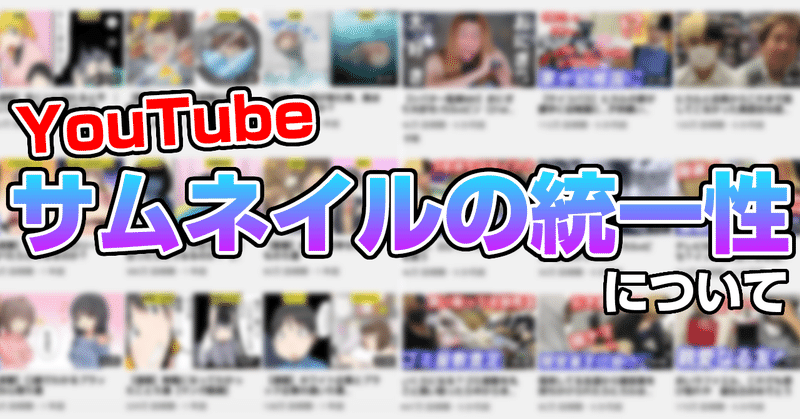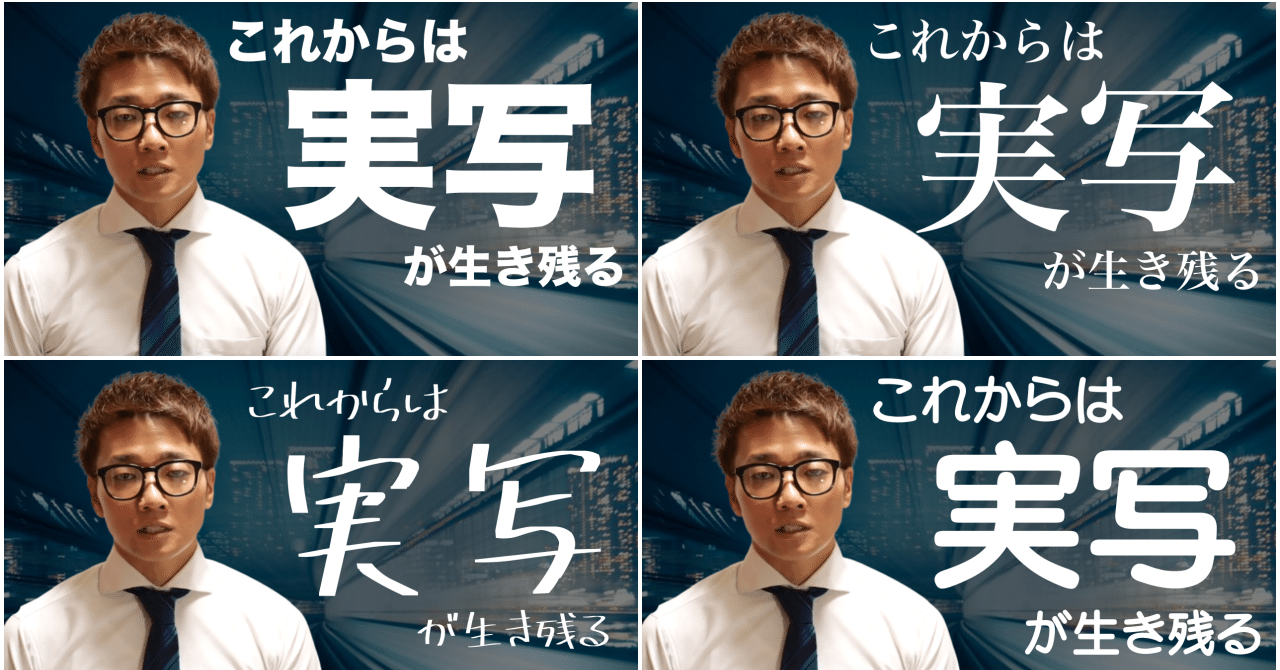
Youtube サムネイル 文字 フォント
サムネイル作り方のコツ4フォント・文字色にもこだわる サムネイルを作る際には、フォントや文字色にもこだわりましょう。 見た目の印象が全く異なるからです。 東海オンエアの2つの動画を例に挙げて説明していきます。 こちらがフォントや文字色.
Youtube サムネイル 文字 フォント. サムネイルを作っていると、 画像と文字のイメージが一致しなかったり、 なかなか決まらないなんてことありませんか? そこで今回はサムネイル作成にバッチリな無料フォントを一気に. Gimpは 縁取り文字が作れる無料の画像編集ソフト 。 当記事では、サムネイルやアイキャッチ画像での縁取り文字の作り方を動画付きで紹介しています。 最近は画像に文字を入れる手法が流行っていますよね。. サムネイルが大きすぎる場合は文字が切れたり、小さすぎる場合黒い背景が入ったりと手抜き感が出てしまいます。 なお、暴力表現や性的表現、個人情報など、 ユーザーにとって不適切とYouTubeが判断した場合、 サムネイルが無効化されることがあります。.
YouTubeのサムネイル画像を作るときに必要な『3つの重要ポイント』三分割法って! サムネイルにも文字 文字を使う場合は、画面上で読みやすいフォントを使い、文字サイズも調整する. パワーポイントでサムネイルが作れます YouTubeで目を引くサムネイル、キャッチなタイトルは欠かせません。 以前作成した、YouTubeサムネイルの作り方 無料アプリ Skitchを使うも好評ですが、今回は多くの方が使っているパワーポイントでサムネイルを作る方法を解説します。. そもそも『サムネイル』って何?? YouTubeのサムネイルは動画内容より大切! YouTubeのサムネイルのサイズって?? Canva無料でセンスのいいサムネイルが作れる! Canvaが凄い!無料で使える素材やフォントが多い 作例①テンプレのセンスがいいので.
本記事の内容 サムネイルって重要なの? きれいで目をひくサムネイルを作れる画像編集ソフト ゲーム実況. YouTubeのサムネイル画像を作るときに必要な『3つの重要ポイント』三分割法って! サムネイルにも文字 文字を使う場合は、画面上で読みやすいフォントを使い、文字サイズも調整する. まずは、YouTubeのサムネイルに使用するのにおすすめのフォントを10種類ご紹介します。 ヒラギノ角ゴシック シンプルなフォントで、 どんなジャンルでも使いやすく 、 等間隔に文字が並んでいるので非常に読みやすい という特徴があります。.
YouTubeの動画編集で使いやすいフリーフォント ジャンル別解説 実際にユーチューブで文字を入れると 太字でインパクトがあるフォントは サムネイルにも向いてます. 先ず文字のフォントが細く、背景画像に同化するような感じでかなり見づらい。 また、元画像のサイズが小さいため、サムネイルにした時に 左右に隙間が出来ていて不恰好 なものになっています。 この辺りはきちんと画像サイズに合うよう調整すべきです。. ブログのサムネイルを作る上でYouTubeのサムネはとても参考になります。中でも、ラファエルさんのサムネの作り込みはスゴイですね。とくにサムネで使われている文字のデザインは僕もマネをしたいと思って、「ラファエル サムネ 作り方」「YouTube サムネ 作り方」とかで検索しても、この文字.
フォントのイメージごとにグループを作ることで、様々なYouTube動画で使用されているフォントを簡単に見つけられるように管理しています。 グループの分け方は人それぞれですが、上の画面では、 怖い系、POP、手書き、角ゴシック、毛筆、明朝 に分けてい. こちらのYouTubeサムネイルも、 ボックスと文字を重ねただけのシンプルなデザインになっています。 シンプルなサムネイルながら、 特徴のあるフォントをでおしゃれを演出していますね♪ YouTubeチャンネルはこちら 余白(文字間)の使い方 Takahiro Kawashima. こんにちは、エックスラボの藤です! 今回は、サムネイル画像やテロップづくりに使える日本語フリーフォントを紹介します。 イメージに合うフォントを使う事で、画面全体の雰囲気が洗練されたものになります。 また、言葉の長さによって適切とされるフォン.
こちらのYouTubeサムネイルも、 ボックスと文字を重ねただけのシンプルなデザインになっています。 シンプルなサムネイルながら、 特徴のあるフォントをでおしゃれを演出していますね♪ YouTubeチャンネルはこちら 余白(文字間)の使い方 Takahiro Kawashima. 「フォント」は太いゴシックに「文字 Youtubeでサムネイルが設定出来ない。 サムネイルのサイズは?解像度は? 変更はできるの? こんな疑問に答える記事です。 こんなことが書かれています。 カ. Youtuberのサムネイル文字を真似して画像に入れてみる それではまずはYoutuberの文字を参考にサムネイルを作っていきましょう! ここはまずリスペクトを込めてレペゼン地球さんのYoutubeサムネイルの文字を参考にさせていただきます。.
また和文フォントの場合には文字の間が不自然に感じる場合がありますので気になったら修正しておきましょう。 Youtubeでサムネイルが設定出来ない。 サムネイルのサイズは?解像度は? 変更はできるの? こんな疑問に答える記事です。 こんなことが. YouTubeチャンネルを運営している人なら、サムネイルに使用するフォントで悩んだ経験がある人も多いのではないでしょうか? 動画の内容に加え、フォントも目立つサムネイルにすれば あなたのチャンネルの印象アップ !. また和文フォントの場合には文字の間が不自然に感じる場合がありますので気になったら修正しておきましょう。 Youtubeでサムネイルが設定出来ない。 サムネイルのサイズは?解像度は? 変更はできるの? こんな疑問に答える記事です。 こんなことが.
② で文字のフォント YouTubeのサムネイルをダウンロードしたい人は結構いるんじゃないでしょうか? 例えば、YouTubeアフィリエイトを攻略するためには、リサーチを行って参考になるチャンネルや動画を真似(参考に)していくというのが王道なわけです。. YouTubeのサムネイルを作りたいけど、 有料の画像編集ソフトは買いたくない 。そう考えてるあなたへ・・・ そこで今回は、ブラウザ上で使える「 無料ツール『Canva』 」を使った、サムネイルの使い方を紹介します。.